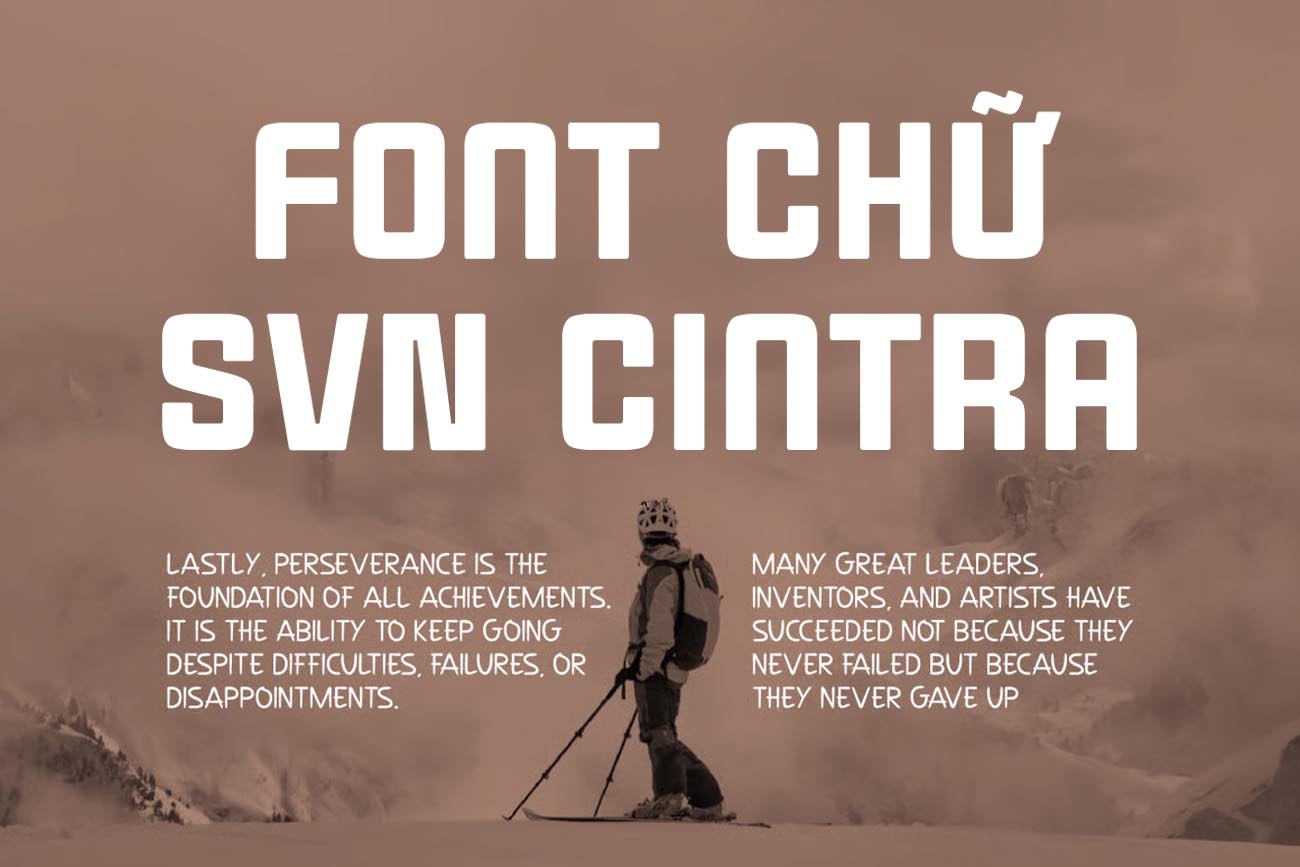
Tải Miễn Phí - Font Chữ SVN Cintra Mạnh Mẽ, Hiện Đại & Việt Hóa Chuẩn
Tác giả Pedro Alexandre Teixeira
Việt hóa Team SVN
SVN-Cintra là bộ font chữ không chân được Việt hóa từ kiểu chữ Cintra nổi tiếng do Pedro Alexandre Teixeira thiết kế. Mang phong cách geometric sans-serif, font có những đường nét vuông vức, góc cạnh và đối xứng, tạo cảm giác cứng cáp và chuyên nghiệp. Đây là lựa chọn lý tưởng cho các dự án đòi hỏi sự hiện đại, kỹ thuật và tối giản.
Điểm nổi bật của font chữ mạnh mẽ này nằm ở kiểu dáng mang tính công nghiệp, dễ đọc và dễ ứng dụng trong nhiều định dạng: từ thiết kế logo, poster công nghệ đến giao diện website hay bao bì sản phẩm. Font đã được Việt hóa đầy đủ bởi đội ngũ SVN, hỗ trợ dấu tiếng Việt rõ ràng, không lỗi ký tự, đảm bảo chất lượng sử dụng cao.
Nếu bạn đang tìm kiếm một font chữ kỹ thuật vừa hiện đại, vừa dễ dùng cho thiết kế thương hiệu nam tính, bảng hiệu kỹ thuật số hay tài liệu khoa học – SVN-Cintra là lựa chọn bạn không nên bỏ qua.